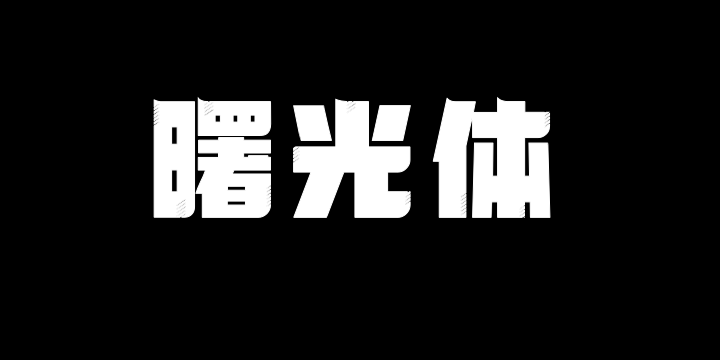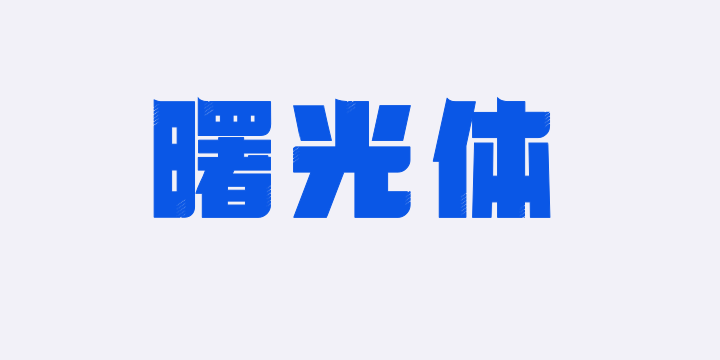
上首曙光体 By 上首造字 商用字体
字体全名: 上首曙光体
铸字厂: 上首造字
设计师: 胡博剑
字体简介: 上首曙光体,笔画硬朗简洁,富有现代感的同时具有力量感。其设计灵感源自在宇宙中光速穿梭的机械飞船,划破黑暗,带来曙光,象征着科技、希望与新生。在创作过程中,设计师从飞船的形态与气质中汲取灵感,将机械的锐利与明亮感融入字体笔画之中,赋予字体独特的视觉张力。在结构上,上首曙光体注重简洁与平衡,既保留了传统字体的稳健根基,又大胆运用现代设计手法,使字体线条更加流畅、明快。这种设计既符合当下快节奏的信息时代对字体识别性的要求,又能在视觉上给人带来焕然一新的感受。上首曙光体不仅展现了现代设计的创新精神,还考虑到实际应用中的功能性需求。适用于搭配标志、广告标语、商业广告等高端属性。